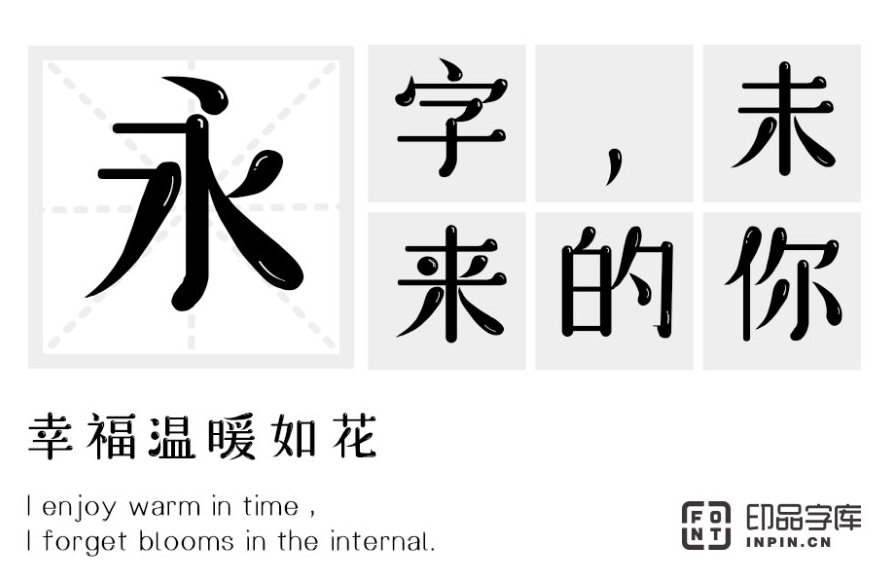
"萌萌哒"是一个网络词汇,有"太可爱了"的含义,也可以形容某种表现形式。
在生活中,我们常用胖墩墩、可爱来描述小宝宝,用憨态可掬、萌翻了形容小动物,形态呆萌萌、娇滴滴 、肥嘟嘟,白白胖胖充满希望的模样 ,都赋予了它萌萌哒的属性 ,这张 图片字体就是萌萌哒风格,在母婴、儿童相关的设计中广泛被应用。
印品溜溜圆字体,笔画整体圆润,亲和力十足。在笔画密集的位置做出了细节修改,让字体空间更透气,层次感丰富。 不完全是横平竖直规矩的线条感,展现出保持童心的执着,俏皮的断笔处理起到调和的作用。 整体展现风格活泼松弛、圆润有度。适用于面广阔,可用于广告设计、包装设计、logo设计、海报设计、屏幕显示等。